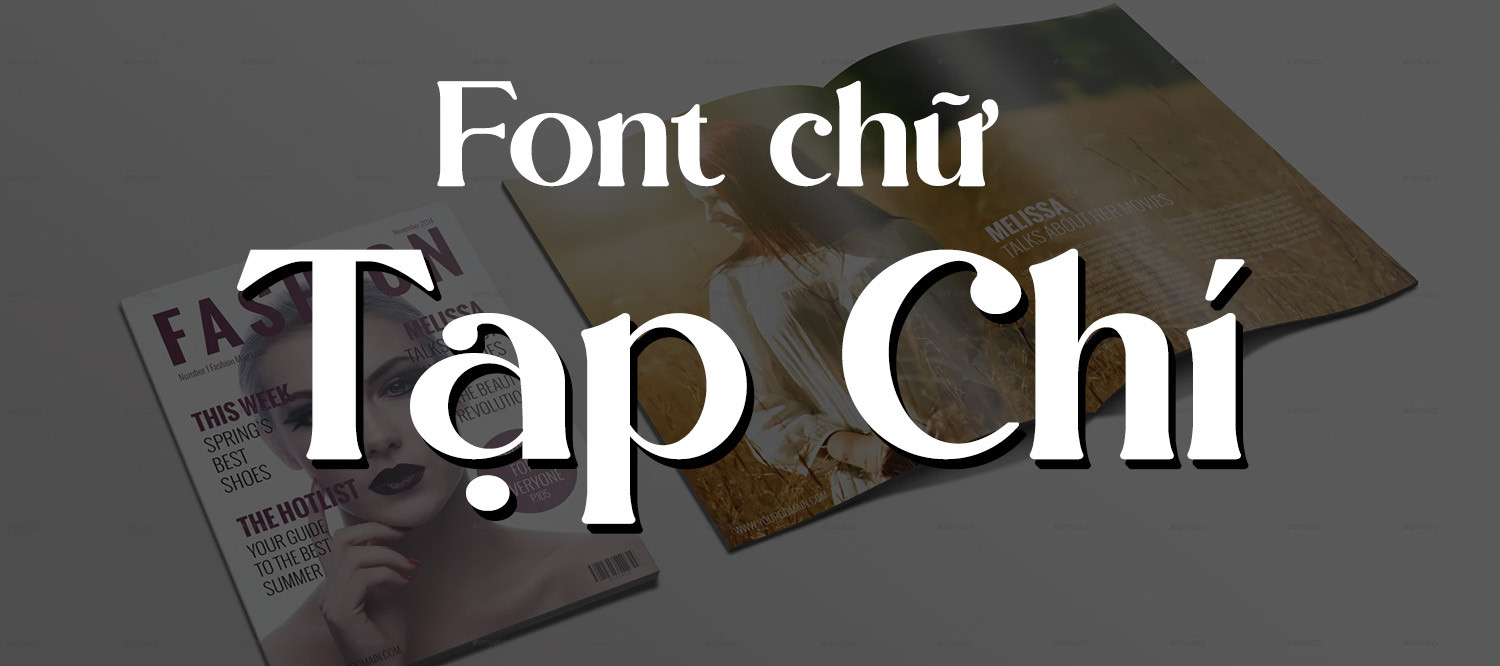
Font chữ tạp chí là những kiểu chữ được sử dụng trong thiết kế và trình bày nội dung của các tạp chí. Những font chữ này thường phải đảm bảo tính thẩm mỹ cao, dễ đọc và phù hợp với phong cách và nội dung của tạp chí. Font chữ tạp chí thường được chia thành hai loại chính: font chữ tiêu đề và font chữ nội dung.
Font chữ tiêu đề: Đây là những font chữ được sử dụng cho tiêu đề bài viết, các mục lục chính hoặc các phần cần nhấn mạnh. Những font chữ này thường có kích thước lớn, kiểu dáng độc đáo và thu hút sự chú ý của người đọc. Chúng có thể mang phong cách hiện đại, cổ điển, sang trọng hoặc vui nhộn, tùy thuộc vào chủ đề và đối tượng độc giả của tạp chí. Một số font chữ tiêu đề phổ biến có thể kể đến như Helvetica, Futura, và Didot.
Font chữ nội dung: Đây là những font chữ được sử dụng cho phần văn bản chính của bài viết. Yếu tố quan trọng nhất của font chữ nội dung là tính dễ đọc và sự thoải mái cho người đọc khi xem trong thời gian dài. Các font chữ nội dung thường có kiểu dáng đơn giản, rõ ràng và khoảng cách giữa các ký tự hợp lý. Các font chữ không chân (sans-serif) như Arial, Helvetica và font chữ có chân (serif) như Times New Roman, Georgia là những lựa chọn phổ biến cho phần nội dung.
Ngoài ra, sự kết hợp hài hòa giữa các font chữ tiêu đề và font chữ nội dung cũng đóng vai trò quan trọng trong việc tạo nên sự hấp dẫn và chuyên nghiệp cho tạp chí. Các nhà thiết kế thường chọn các font chữ phù hợp với phong cách chung của tạp chí, đồng thời đảm bảo sự nhất quán và dễ đọc để mang lại trải nghiệm tốt nhất cho độc giả.
Dưới đây là 10 font chữ để thiết kế tạp chí đẹp nhất hiện tại. Phù hợp cho mọi chủ đề, đã được bên S99.VN lựa chọn cẩn thận
SVN-Kontras là một font chữ hiện đại và sang trọng, được thiết kế đặc biệt cho các tạp chí thời trang và các ấn phẩm cao cấp. Với các đường nét thanh thoát, tinh tế và sự cân đối hoàn hảo, SVN-Kontras mang đến vẻ đẹp đẳng cấp và thu hút ngay từ cái nhìn đầu tiên. Font chữ này không chỉ dễ đọc mà còn tạo nên phong cách chuyên nghiệp và thời thượng, phù hợp cho tiêu đề, nội dung và các mục nổi bật trong tạp chí. SVN-Kontras giúp các thiết kế trở nên ấn tượng và đậm chất thời trang.
TH Des Morgan là một font chữ thanh lịch và hiện đại, lý tưởng cho các tạp chí cao cấp và các ấn phẩm thời trang. Với thiết kế tinh tế, các đường nét sắc sảo và cân đối, TH Des Morgan mang lại vẻ đẹp trang nhã và đẳng cấp. Font chữ này không chỉ đảm bảo tính dễ đọc mà còn tạo nên phong cách chuyên nghiệp và thời thượng cho các bài viết và tiêu đề. TH Des Morgan phù hợp để sử dụng cho cả nội dung chính và các tiêu đề nổi bật, giúp mỗi trang tạp chí trở nên cuốn hút và sang trọng.
TH Megan là một font chữ mang đậm phong cách thanh lịch và sang trọng, hoàn hảo cho các thiết kế tạp chí cao cấp. Với các đường nét tinh tế, mềm mại và sự cân đối tuyệt vời, TH Megan tạo nên vẻ đẹp trang nhã và đẳng cấp cho bất kỳ ấn phẩm nào. Font chữ này không chỉ dễ đọc mà còn góp phần nâng tầm phong cách chuyên nghiệp và thời thượng cho các bài viết và tiêu đề. TH Megan lý tưởng để sử dụng cho các tiêu đề nổi bật, nội dung chính và các mục đặc biệt, giúp mỗi trang tạp chí trở nên cuốn hút và ấn tượng.
TH Kayonest là một font chữ hoàn hảo mang đậm phong cách thanh lịch và hiện đại, lý tưởng cho các thiết kế thiệp cưới, thời trang và tạp chí. Với các đường nét mềm mại, tinh tế và sự cân đối hoàn hảo, TH Kayonest tạo nên vẻ đẹp trang nhã và đầy cuốn hút. Font chữ này không chỉ dễ đọc mà còn giúp tăng thêm vẻ sang trọng và đẳng cấp cho bất kỳ ấn phẩm nào. TH Kayonest phù hợp để sử dụng cho các tiêu đề, nội dung chính và các mục đặc biệt, mang lại cảm giác chuyên nghiệp và thời thượng cho mỗi thiết kế, từ thiệp cưới đến tạp chí thời trang.
TH Huova Light là một font chữ lý tưởng với phong cách thanh lịch và tinh tế, hoàn hảo cho các thiết kế thiệp cưới, thời trang và tạp chí. Với các đường nét mỏng manh, mềm mại và cân đối, TH Huova Light tạo nên vẻ đẹp nhẹ nhàng, trang nhã và hiện đại. Font chữ này không chỉ dễ đọc mà còn mang lại sự sang trọng và đẳng cấp cho mọi ấn phẩm. TH Huova Light phù hợp cho các tiêu đề, nội dung chính và các mục đặc biệt, giúp mỗi thiết kế trở nên cuốn hút và chuyên nghiệp, từ thiệp cưới lãng mạn đến tạp chí thời trang thời thượng.
SVN-Magnificent là một font chữ với nét mỏng, mang đậm phong cách sang trọng và hiện đại, hoàn hảo cho các thiết kế tạp chí và thời trang cao cấp. Với các đường nét thanh mảnh, tinh tế và sự cân đối tuyệt vời, SVN-Magnificent tạo nên vẻ đẹp thanh lịch và đẳng cấp cho bất kỳ ấn phẩm nào. Font chữ này không chỉ dễ đọc mà còn góp phần nâng tầm phong cách chuyên nghiệp và thời thượng cho các bài viết và tiêu đề. SVN-Magnificent lý tưởng để sử dụng cho các tiêu đề nổi bật, nội dung chính và các mục đặc biệt, giúp mỗi trang tạp chí trở nên cuốn hút và ấn tượng.
SVN-Megante là một font chữ hiện đại, hoàn hảo cho các thiết kế tạp chí và thời trang cao cấp. Với các đường nét thanh mảnh, sắc sảo và sự cân đối tuyệt vời, SVN-Megante mang đến vẻ đẹp sang trọng và tinh tế cho mọi ấn phẩm. Font chữ này không chỉ dễ đọc mà còn góp phần tạo nên phong cách chuyên nghiệp và đẳng cấp cho các bài viết và tiêu đề. SVN-Megante lý tưởng để sử dụng cho các tiêu đề nổi bật, nội dung chính và các mục đặc biệt, giúp mỗi trang tạp chí trở nên cuốn hút và ấn tượng, thể hiện rõ nét sự hiện đại và thời thượng.
Link tải: Link
SVN-Saudagar là một font chữ hiện đại và sang trọng, hoàn hảo cho các thiết kế trong lĩnh vực tạp chí và thời trang. Với các đường nét thanh mảnh, tinh tế và sự cân đối hoàn hảo, SVN-Saudagar mang lại vẻ đẹp đẳng cấp và cuốn hút cho mọi ấn phẩm. Font chữ này không chỉ dễ đọc mà còn tạo nên phong cách chuyên nghiệp và thời thượng, lý tưởng cho các tiêu đề nổi bật, nội dung chính và các mục đặc biệt. SVN-Saudagar giúp mỗi trang tạp chí và thiết kế thời trang trở nên ấn tượng và tinh tế, phản ánh sự hiện đại và sang trọng của lĩnh vực này.
Link tải: Link
TH Moglan là một font chữ mang đậm phong cách thanh lịch, hiện đại và sang trọng, lý tưởng cho các thiết kế tạp chí cao cấp. Với các đường nét tinh tế, cân đối và sắc sảo, TH Moglan tạo nên vẻ đẹp trang nhã và cuốn hút cho mọi ấn phẩm. Font chữ này không chỉ đảm bảo tính dễ đọc mà còn góp phần nâng tầm phong cách chuyên nghiệp và thời thượng cho các bài viết và tiêu đề. TH Moglan phù hợp cho các tiêu đề nổi bật, nội dung chính và các mục đặc biệt, giúp mỗi trang tạp chí trở nên ấn tượng và đầy phong cách, thể hiện rõ sự tinh tế và đẳng cấp.
Link tải: Link
TH Leky Calgria là một font chữ thanh lịch và sang trọng, lý tưởng cho các thiết kế đòi hỏi sự tinh tế và đẳng cấp. Với các đường nét mềm mại, cân đối và sự tinh tế trong từng chi tiết, TH Leky Calgria mang đến vẻ đẹp trang nhã và cuốn hút cho mọi ấn phẩm. Font chữ này không chỉ dễ đọc mà còn tạo nên phong cách chuyên nghiệp và thanh lịch, phù hợp cho các dự án thiết kế như thiệp cưới, tạp chí thời trang, và các tài liệu quảng cáo cao cấp. TH Leky Calgria giúp mỗi thiết kế trở nên nổi bật và thể hiện rõ sự sang trọng và tinh tế.
Link tải: Link
Lưu Ý Khi Chọn Font Chữ Tạp Chí Khi Thiết Kế
Chọn font chữ phù hợp là một yếu tố quan trọng trong thiết kế tạp chí. Dưới đây là một số lưu ý quan trọng giúp bạn chọn được font chữ lý tưởng cho tạp chí của mình:
Tính Dễ Đọc:
Font chữ cần phải dễ đọc để người đọc có thể dễ dàng tiếp nhận thông tin. Tránh sử dụng các font chữ quá phức tạp hoặc trang trí quá mức.
Phong Cách Phù Hợp:
Lựa chọn font chữ phù hợp với phong cách và chủ đề của tạp chí. Ví dụ, một tạp chí thời trang cao cấp có thể sử dụng các font chữ thanh lịch và sang trọng, trong khi một tạp chí thiếu nhi có thể dùng font chữ vui nhộn và thân thiện.
Kết Hợp Font Chữ:
Sử dụng một hoặc hai font chữ chính để tạo sự nhất quán. Kết hợp các font chữ tiêu đề và nội dung để tạo sự hài hòa. Tránh sử dụng quá nhiều loại font chữ trong cùng một thiết kế.
Kích Thước Font Chữ:
Đảm bảo kích thước font chữ phù hợp với nội dung. Tiêu đề nên có kích thước lớn hơn để tạo điểm nhấn, trong khi phần nội dung chính cần kích thước vừa phải để dễ đọc.
Khoảng Cách và Dãn Dòng:
Điều chỉnh khoảng cách giữa các ký tự và dãn dòng để đảm bảo văn bản dễ đọc và không gây mỏi mắt cho người đọc.
Màu Sắc:
Chọn màu sắc font chữ tương phản với nền để tăng cường tính dễ đọc. Tránh sử dụng màu sắc quá chói hoặc không phù hợp với tổng thể thiết kế.
Tính Đồng Nhất:
Đảm bảo sự đồng nhất về font chữ trong toàn bộ tạp chí. Điều này giúp tạo ra một trải nghiệm đọc liền mạch và chuyên nghiệp.
Độ Dày và Kiểu Chữ:
Sử dụng các biến thể khác nhau của font chữ (như đậm, nghiêng, in hoa) để tạo sự nhấn mạnh và phân biệt giữa các phần khác nhau của nội dung.
Thử Nghiệm và Đánh Giá:
Thử nghiệm nhiều font chữ khác nhau và đánh giá hiệu quả trực quan của chúng. Yêu cầu ý kiến từ đồng nghiệp hoặc độc giả để chọn được font chữ tối ưu nhất.
Những lưu ý này sẽ giúp bạn chọn được font chữ phù hợp nhất cho tạp chí của mình, tạo nên sự thu hút và chuyên nghiệp cho từng trang nội dung.